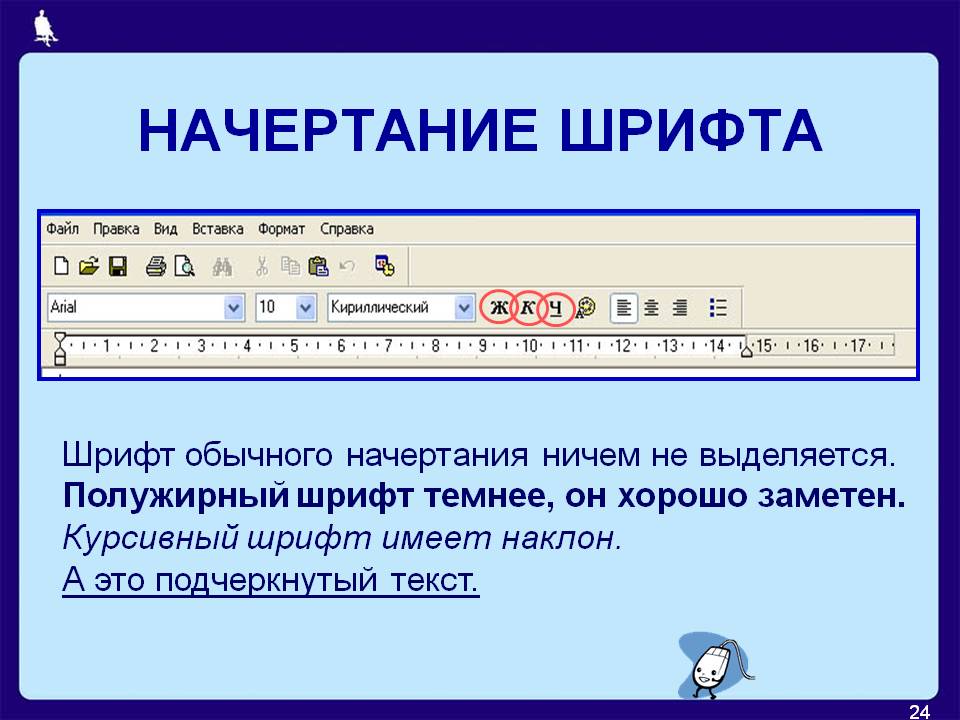
«Почему в Word полужирный шрифт есть, а жирного нет?» — Яндекс Кью
Надо уточнить, что здесь речь идёт прежде всего о кнопочке B, в которую зашит некий функционал. Вы должны понимать, что в Word есть ровно те шрифты и те начертания — те насыщенности, — которые вы установили себе в операционную систему. А вопрос здесь касается именно функционала Word и того, что пришивается по умолчанию к этой кнопочке B.
Второй частью этого вопроса является русская терминология в целом и то, почему слово bold соответствует слову полужирный, хотя, казалось бы, это вполне жирное начертание. Здесь всё дело заключается в том, что русская терминология в области типографики и шрифта довольно богатая, однако не столь богатая, как английская. И в диджитал-эпоху это мало как поменялось: она унаследовала терминологию всех предыдущих технологических этапов развития типографики. Есть прямое начертание, есть курсивное; оба они могут быть разной насыщенности, в том числе жирной, то начертание, которое в английском языке соответствует термину bold и в русской традиции называется полужирным. У нас не так много терминов, которые могли бы эти разные насыщенности отображать. В английском языке целая градуировка: есть начертание thin, есть начертание light, есть начертания regular, book, medium, extra bold, bold и так далее. Русской типографике приходится чаще всего просто опираться на этот терминологический словарь английского, потому что собственных терминов у нас меньше.
Но и с точки зрения градации в английском, жирное начертание скорее соответствует начертанию black или начертанию heavy — чему-то очень насыщенно жирному. Именно поэтому болду, который в общей шкале жирности не самое жирное начертание, у нас соответствует термин «полужирный».
Ворд в первую очередь шрифтовой редактор для документов. Все жирные, ультра и экстра жирные, как и экста тонкие (light, condensed) ему не нужны, потому что эти начертания относятся к акцидентным (плакатным) шрифтам и имеют изобразительную ценность. То есть доп. начертания не нужны потому что в мелком кегле (размере) теряют свои свойства удобочитаемости, потому и… Читать далее
Как использовать полужирный шрифт, курсив и подчеркивание в Twitter
Распространенный вопрос среди многих пользователей: как использовать жирный шрифт, курсив и подчеркивание в Твиттерето есть, какие шаги необходимо предпринять, чтобы текст в публикациях в социальной сети выглядел отформатированным.
Мало кто прибегает к этому просто по незнанию, но на самом деле возможность форматировать текст имеет большую актуальность, так как благодаря этому вы можете быстро изменить стиль письма, как в биографии, так и в имени или твитах, где это имеет большее значение.
Использование жирных, курсивных или подчеркнутых букв может значительно помочь твитам социальных сетей выделиться в глазах тех, кто их просматривает. Ключевое слово, выделенное жирным шрифтом, всегда будет выделяться больше, чем, например, если это не так.
Как использовать полужирный, курсив и подчеркивание в Твиттере
Если вы хотите знать, как использовать жирный шрифт, курсив и подчеркивание в ТвиттереМы собираемся поговорить о нескольких приложениях, которые вы можете использовать для этого, которые очень просты и удобны в использовании, поэтому не составит труда запустить их в работу для дальнейшей персонализации ваших твитов. Эти приложения следующие:
Стильный текст
Стильный текст это приложение, которое имеет большое количество очень оригинальных буквенных шрифтов, которые позволят вам изменить весь стиль ваших твитов, а также биографию или ваше имя пользователя, очень простое в использовании и позволяющее размещать текст так же, как вы хотите, выделяя его среди остальных публикаций.
Чтобы начать его использовать, вы должны сначала зайти в магазин приложений вашего смартфона и найти приложение. Стильный текст. Когда вы это сделаете, на экране появится руководство, в котором будет показано, как работает приложение. После этого вы можете закрыть приложение и открыть Twitter.
В этом смысле вам нужно будет только перейти к отредактируйте свой профиль в Twitter или напишите новый твит, в зависимости от того, где вы хотите использовать эти разные текстовые шрифты.
Чтобы изменить шрифт текста, вы должны написать его обычным способом, а затем выбрать слово или фазу для изменения. При нажатии и удерживании появятся различные параметры, такие как поиск, перевод и Стильный текст, который вам нужно будет нажать.
Как только вы это сделаете, вы сможете выбрать тип шрифта, который вам больше всего нравится, и вы увидите, как автоматически изменяется текст в соответствии с вашими предпочтениями и тем, что вы действительно выбрали.
шрифты
шрифты — еще одно альтернативное приложение, которое вы можете использовать для изменения своего текста, хотя на этот раз, помимо использования его в Twitter, вы можете сделать то же самое в Instagram или WhatsApp, поэтому оно предлагает вам больше возможностей. Он работает для этих социальных сетей, потому что состоит из клавиатуры, которая обеспечивает различные шрифты букв.
Вы должны помнить, что, будучи клавиатурой, она может записывать то, что вы вводите, например, номера телефонов, номера счетов, адреса, пароли и т.
Д.
Первое, что вам нужно сделать, это зайти в магазин приложений и загрузить приложение на свой мобильный телефон. Затем вы должны нажать на Включить шрифты клавиатуры, что приведет вас к настройкам мобильного телефона, чтобы вы могли включить шрифты в качестве клавиатуры по умолчанию.
Затем вы должны вернуться и нажать «Перейти на шрифты«, скоро шрифты и позже вам придется написать то, что вы хотите. Затем вы можете выйти из приложения, открыть Twitter и создать текст, который вы хотите в твите или в биографии профиля Twitter, а также в другой социальной сети, если вы хотите использовать этот тип текста также в других социальных сетях, таких как WhatsApp или Инстаграм.
Если вы хотите перейти на обычную клавиатуру Google или любую другую, которую хотите использовать, вам просто нужно щелкнуть значок, представленный мировым шаром на клавиатуре, откуда вы можете выбирать между различными клавиатурами, которые вы установили, в том числе тот, который входит в стандартную комплектацию вашей операционной системы или голосовой диктовки.
Таким простым способом вы можете изменить источник Twitter, хотите ли вы поставить полужирный, курсив, подчеркивание или зачеркивание как если бы вы хотели использовать другие типы оригинальных источников, которые могут вас заинтересовать, что позволит вам создавать очень оригинальные тексты и биографии, которые могут отличаться от остальных публикаций.
Полезные ярлыки для Twitter
Twitter — одна из важнейших социальных сетей в мире, позволяющая использовать различные сочетания клавиш которые очень полезны для выполнения различных действий в социальной сети, которые могут быть вам очень полезны.
По этой причине мы пользуемся возможностью поговорить с вами о различных действиях, которые вы можете использовать, чтобы получить максимальную отдачу от платформы и удобным способом.
Действия
- n: Новый твит.
- l: Мне нравится открытый твит.
- r: Ответ на открытый твит
- m: Личное сообщение.
- u: Отключить аккаунт.
- b: Заблокировать учетную запись.
- Главная: Открыть подробную информацию о твите.
- o: Развернуть фото.
- /: Искать.
- Control + Enter: Отправьте твит, который вы написали.
навигация
- ?: Открыть контекстное меню.
- j: Следующий твит
- k: Предыдущий твит.
- Пробел: Листать вниз
- Точка (.): Загрузить больше твитов.
хронология
- г + ч: Перейти на нашу временную шкалу
- г + о: Моменты.
- г + п: Уведомления.
- г + г: Упоминания.
- г + п: Профиль.
- г + л: Нравится таб.
- г + я: Вкладка «Списки».
- г + м: Лоток для прямых сообщений.
- г + с: Настройки и конфиденциальность.
- г + ты: Поисковая система открывается для поиска конкретного пользователя.
Эти сочетания клавиш очень полезны для Twitter, так что вы можете заметно улучшить свой опыт в социальной сети, одной из самых популярных в течение многих лет в сети, поэтому вы должны принять это во внимание, если хотите поделиться мнениями или опубликовать свою компанию , деятельность или бизнес.
Статья о полужирном+шрифте от The Free Dictionary
Жирный+шрифт | Статья о жирном+шрифте от The Free Dictionary
Слово, не найденное в Словаре и Энциклопедии.
Возможно, Вы имели в виду:
Пожалуйста, попробуйте слова отдельно:
полужирный шрифт
Некоторые статьи, соответствующие вашему запросу:
- Futura (шрифт)
- Шрифт (типографский термин)
- Times Roman
- Оригинальный составной шрифт
- шрифт
- News Gothic
- Основные шрифты для Интернета
- Arial
- Gentium
- Шрифты PostScript
- Список шрифтов в Mac OS X
- Eurostile
- Шрифт Expert
- Gill Sans
- Microgramma (гарнитура)
Полный браузер ?
- ▲
- ЖИРНЫЙ FMRI
- полужирный шрифт
- Смелый Forbes
- Экстраполяция жирным шрифтом от руки
- Смелый в Боге
- жирный разрез
- Смелое путешествие
- Смелый переулок
- Новая смелая графика
- Семинар для смелых родителей
- Смелый парк
- Смелый парк (Западная Австралия)
- Водохранилище Болд Парк
- Смелый пилот
- Смелая линейка
- Смелая улица, Ливерпуль
- Книги о смелых штрихах
- Жирный текст
- Жирный шрифт
- Смелое предприятие
- полужирный+шрифт
- полужирный, курсив, подчеркнутый
- Жирный, Мерсисайд
- Смелый, неприятный, надежный и всегда быстрый
- Смелый, оригинальный, кухонный артистизм
- Жирный, Сент-Хеленс
- полужирный
- наглый лжец
- наглая ложь
- смело
- жирный шрифт
- Болда
- ЖИРНЫЙc
- Земля Болдекер
- Болдеков
- Болден
- Болден Реуш Харрисон
- Болден, Бадди
- Болденон
- смелее
- Смелые велосипедисты
- Смелый валун
- Смелый мост Барнсли
- Зона отдыха Болдер Дам
- Смелее Медиа
- Более смелое профессиональное размещение
- Кампус Болдервуда
- ▼
Сайт: Следовать:
Делиться:
Открыть / Закрыть
Жирный шрифт и толстые шрифты
Веб-дизайн и разработка
Эллисон Рид 2 апреля 2022 г.
Жирный шрифт обладает невероятным потенциалом при правильном использовании, то есть в нужном месте и в нужном количестве. В этой статье мы собрали лучшие советы от ведущих веб-дизайнеров о том, как и где применять жирный шрифт. Узнав о качествах (не)уместного полужирного текста, мы предложим вам десять бесплатных полужирных шрифтов, принадлежащих к числу наших любимых. Продолжайте читать, чтобы узнать больше об основных преимуществах жирного шрифта, а также о рисках, связанных с использованием жирного шрифта.
Подходящий жирный шрифт: зачем использовать жирный шрифт
Причина 1. Начнем с того, что есть только одна истинная причина, по которой вам нужны жирные буквы на вашем сайте. И эта основная причина заключается в том, чтобы выделить . Другими словами, правильный способ использования жирного шрифта — это указать контент, который необходимо выделить, и выбрать соответствующие толстые шрифты.
Причина 2. Толстые шрифты также можно использовать для демонстрации визуальной иерархии на веб-странице.
Это особенно важно для многостраничных сайтов, содержащих длинные описания. Короче говоря, жирный шрифт может служить ориентиром, когда документ или страница выглядят перегруженными информацией.
При этом вы должны помнить, что есть и другие эффективные инструменты, которые можно использовать для этой цели, такие как подчеркивание, больший размер шрифта, курсив, пробелы, таблицы и т. д. Задайте себе вопрос, почему толстые шрифты, а не давайте скажем, шапки. Вы хотите использовать жирный шрифт без уважительной причины (или, другими словами, «Сейчас он выглядит более привлекательным для меня» и «Вот так я вижу свой веб-сайт») или чтобы подчеркнуть определенную мысль? Если ваш ответ подразумевает «подчеркнуть суть», то дерзайте — найдите жирный шрифт и используйте его! Если нет, то, очевидно, вам следует пересмотреть применение жирного шрифта в своем онлайн-проекте.
Причина 3. Еще одна причина для добавления жирного шрифта на ваш веб-сайт – это привлечение большего внимания ваших потенциальных посетителей в Интернете.
Но опять же, пояснительные видео и галереи могут быть гораздо полезнее, чем простой жирный текст в этом случае, не так ли? Так что не заблуждайтесь — с первого дня должно быть четкое понимание роли полужирных шрифтов на вашем сайте.
Причина 4. Также стоит отметить, что жирный шрифт используется для обеспечивают высокую читаемость . Уже научно доказано, что люди в первую очередь замечают (и читают) текст, напечатанный крупным шрифтом. В сочетании с минималистичным дизайном люди не могут не читать жирные буквы.
Подходящий жирный текст: где использовать полужирный шрифт
Хорошее место для начала тестирования полужирных шрифтов — заголовок. Это то место, где ваши онлайн-клиенты ожидают увидеть жирный текст, так зачем их разочаровывать? Добавление жирных букв в заголовок обычно делает акцент на ваших дизайн логотипа и слоган компании . В результате эти два элемента по психологии шрифта легче запоминаются и распознаются.
Конечно, эта маркетинговая стратегия будет работать, только если вы используете жирный и нейтральный текст в разумных пропорциях.
Более того, всегда имеет смысл выбирать жирный шрифт при разработке заголовков для сообщений в блоге. Создавая потрясающее сочетание классики и современности, смелые шрифты способны привлечь внимание посетителя онлайн, как никакой другой инструмент типографики.
Еще один элемент контента, который можно выделить жирным шрифтом, — это строки перехода , например «Подробнее» или «Продолжение со страницы 1». Направление ваших онлайн-посетителей к следующей/предыдущей части вашего текущего сообщения в блоге с помощью элегантной кнопки может принести вам дополнительные клики. В результате жирные шрифты могут улучшить конверсию на вашем сайте.
Неуместный жирный текст: Плохая жирная типографика
Есть несколько случаев, когда жирный шрифт воспринимается негативно. Среди них:
Слишком жирный шрифт
Как вы прочитали выше, жирный шрифт следует использовать для выделения важной информации.
Если вы используете эти шрифты слишком интенсивно, вы можете столкнуться с онлайн-посетителями, которые слишком дезориентированы, чтобы обращать внимание на какой-либо ваш контент. Итак, убедитесь, что вы правильно определили важную информацию и сделали ее визуальным центром вашего сайта.
Too Longy BoldText
Если вы планируете выделить несколько слов (до 6) жирным шрифтом, подумайте еще раз. визуальная стимуляция работает только тогда, когда она сопровождается содержательным нейтральным содержанием.
Перекрывающийся акцент
Как мы уже упоминали выше, существует множество различных инструментов для демонстрации иерархии на веб-странице. Смелая типографика — просто один из них. Однако, когда вы выбираете жирный шрифт, рекомендуется свести к минимуму использование других (часто перекрывающихся) инструментов для выделения. И, конечно же, нет необходимости комбинировать какие-либо из них. Поверьте мне, когда я говорю, что подчеркнутый жирный курсив можно определить как катастрофу веб-дизайна.
Несовместимые толстые буквы
Если вы решили, что жирные шрифты должны стать неотъемлемой частью вашего веб-сайта, постарайтесь сохранить их только для особых случаев. Выберите веб-элемент, который будет выделен жирным шрифтом, и придерживайтесь его. Не вводите в заблуждение своих онлайн-посетителей несоответствиями, например наличием жирного логотипа на странице «О нас» и нейтрального логотипа на всех остальных страницах. Теперь, когда вы полностью осведомлены о преимуществах жирного шрифта, не стесняйтесь просматривать коллекцию бесплатной жирной типографики.
10 бесплатных толстых шрифтов
Abro Sans — Editorial Sans Serif Font Thin to Bold
Anson Free Sans Serif Font
ADAM.CG PRO
9 0005
Godnes — Бесплатный уникальный шрифт
Шрифт Thiket
Cred — единственный в своем роде жирный шрифт
Renual Contemporary Loud and Bold Typography
Psycho Font
Fela – Бесплатный шрифт для личного и коммерческого использования
Шрифт Mortar Brush
MotoCMS также выбирает шрифт Bold
Наша команда стремится следовать тенденциям и новым дизайнерским решениям, поэтому большинство наших веб-сайтов также выделить жирным шрифтом типография.
При необходимости клиенты могут изменить его стиль, формат и размер в интуитивно понятной панели администратора. Если у вас еще нет сайта, но вы хотите продвигать свои услуги или товары, MotoCMS может предложить вам готовое решение и помочь запустить адаптивный сайт за несколько дней!
Подводя итоги Bold Typography